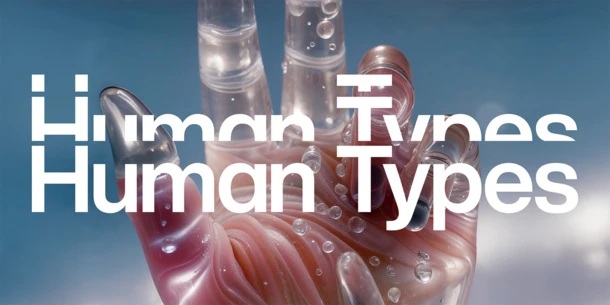
MonotypeがAIプロジェクト「Human Types」を発表。タイポグラフィとグラフィックデザインの世界における、人間とテクノロジーの関係を探求するAIプロジェクトを発足
書体デザインとテクノロジーのグローバルリーダーであるMonotypeは、タイプトレンドRe:Vision 2025の一環として、AIプロジェクト Human Typesを立ち上げたことを2025年6月5日に発表した。
MonotypeRのエグゼクティブ・クリエイティブ・ディレクター、Charles Nix氏とPhil Garnham氏が率いるこのプロジェクトは、人工知能(AI)とタイポグラフィの進化する関係について深く掘り下げ、人工知能がタイプデザインをどのように変えているのか、そして人間の創造性がどのような役割を果たしているかを問いかける。
このプロジェクトは、MonotypeのSina Ott氏、パートナーファウンダリであるBlaze TypeのMatthieu Salvaggio氏、およびMucca、mucca TypoのMatteo Bologna氏の3人が、現代の最も注目すべきデザインの話題について、最新の洞察と見解を共有する。
主なポイント
人間の創造性は依然として不可欠。
Charles Nix氏は次のように述べている。
「デザインは動詞です。デザインは人間的です。それは再構成、革新、実行、キュレーションの活動です」
AIに基づくデザインはすでに存在する。Monotypeによる初期の実験は、AIが驚異的な結果を生み出す能力を示しており、さらなる進歩が見込まれる。
タイポグラフィの豊富さは新しいツールを必要とする。ますます多くのフォントが登場する中で、AIは完璧なフォントのナビゲーションと選択を支援できる。
レタリングがより注目されるようになるだろう。美しい文字の形を創り出すAIの技術は向上し続けるため、より表現力豊かなデザインが可能になる。
タイポグラフィが個人向けにカスタマイズされていく。AIにより、一人一人に合わせたタイポグラフィの体験が提供され、文字との関わり方が変わってくる。
プロジェクトのハイライト
Sina Ott氏:AIで新しい表現の言語を形成
Monotypeのクリエイティブ・タイプ・ディレクターであるSina Ott氏は、AIがもたらす可能性を探る一方で、AIと人間の創造性の関係を深く探り、デザインにおいて人間の直感と感情がどれほどかけがえのないものであるかを強調。
「人間の創造性が革新を推進し、AIがそれを増幅し変化させる」とOtt氏は述べている。
Matthieu Salvaggio氏:AIタイプデザインツールの初期の試み
Blaze Typeの創設者であるMatthieu Salvaggio氏は、β版AIタイプデザインツールを用いて、6つの限定フォントを共同制作した。
「AIを生徒に例えるアイデアから大きな刺激を受けました...そして、その意味では良い結果が得られたと思います」とSalvaggio氏は述べている。
このコラボレーションは、AIの可能性と現在の限界を浮き彫りにした。
Matteo Bologna氏:PapyrusⓇのジレンマ
ブランディングエージェンシーMuccaおよびタイプファウンダリmuccaTypoの創設者Matteo Bologna氏は、個人の忘れられた好みを明らかにするAIの影響について想像しながら、その効果を探求した。BolognaはAIの広範な知識についてジョークを交えて考え、「もしAIが私の世界を支配したら、Papyrusフォントのようなものをいたるところに見せつけてくれるでしょう」と述べている。
※Papyrus:Chris Costelloによってデザインされた書体のこと
Human Typesは、人間のデザイナーとAIが協力して進化していく関係を示すプロジェクト。
このプロジェクトは、創造的なプロセスの中心に人間を置くことを重視しており、AIを単なる手段ではなく、協力と向上を促す道具として位置づけている。
Sina Ott氏は、「AIと一緒に働くことで、私たちはただ文字を制作するだけでなく、新しい表現の言語を創り出します」と述べている。
これは、AIを使って新しい方法でクリエイティブな作業を行うという考えを強調している。